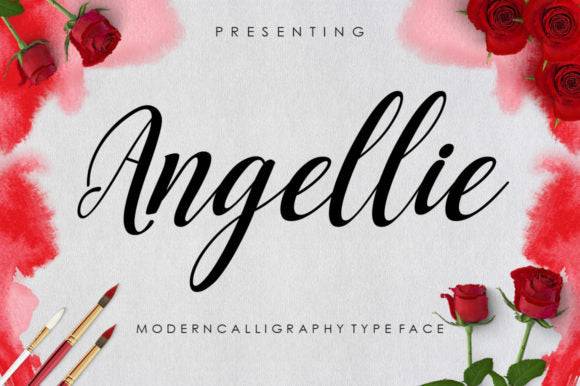
Fuente Angellie para titulares, carteles y proyectos de marca
Angellie es una tipografía refinada para titulares, diseñada para captar la atención en proyectos de branding, editoriales y publicitarios. Presenta líneas limpias, formas definidas y una estructura tipográfica moderna que garantiza que su mensaje destaque tanto en formato impreso como digital.
Esta fuente es ideal para empresas y creadores que buscan un acabado profesional. Angellie se adapta a la perfección a páginas de revistas, banners web y campañas de marca donde la tipografía debe ser elegante y legible.
Ya sea que esté creando una identidad de producto o diseñando para imprimir, Angellie aporta audacia y equilibrio.
Para quién es
- Estrategas de marca y diseñadores de identidad
- Profesionales del diseño de medios impresos y de comunicación
- Creativos publicitarios y equipos de contenido
- Fabricantes de carteles y pancartas
- Diseñadores editoriales y especialistas en marketing digital
Lo que puedes hacer
- Portadas de revistas y anuncios publicitarios
- Carteles, folletos e impresiones promocionales
- Identidades de marca y packaging
- Banners de redes sociales y encabezados web
- Señalización de eventos y elementos visuales de campaña
Por qué te encantará
- Diseño tipográfico moderno y versátil
- Legibilidad de nivel profesional
- Perfecto para formatos de pantalla grandes
- Fuerte jerarquía visual para la marca
P: ¿Qué tipo de fuente es Angellie?
A: Angellie es una fuente de visualización moderna ideal para titulares, carteles y elementos visuales de marca de alto impacto.
P: ¿Esta fuente es buena para materiales impresos de gran tamaño?
R: Sí, Angellie fue diseñado para mantener la claridad y el impacto en tamaños grandes para carteles y señalización.
P: ¿Puedo usar Angellie para gráficos de redes sociales?
R: Definitivamente. Su estructura llamativa la hace perfecta para banners, publicaciones y encabezados de alto contraste.
| Característica | Angellie | Boldara | Titular Nova |
| Estilo de fuente | Titular moderno sin serifa | Exhibición geométrica audaz | Fuente serif editorial |
| Mejores usos | Carteles, marca, titulares | Redes sociales y packaging | Diseño editorial y revistas |